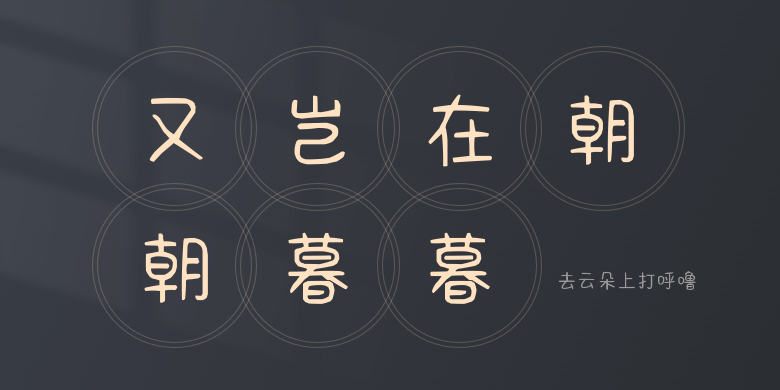
去云朵上打呼噜
去云朵上打呼噜,这款字体结构工整、笔画清晰,兼顾美观与易读性,适用于标题、正文、海报、包装、LOGO 等多种场景。字形优雅稳定,风格百搭耐看,适配日常排版与创意设计,让文字呈现更舒适、更具质感。去云朵上打呼噜一笔一画,皆是细节,以均衡的比例、流畅的线条打造舒适视觉体验,字形端正大气,风格简约现代。无论是商业设计、品牌宣传还是日常排版,都能轻松驾驭,让文字更有格调与力量。去云朵上打呼噜字体下载。